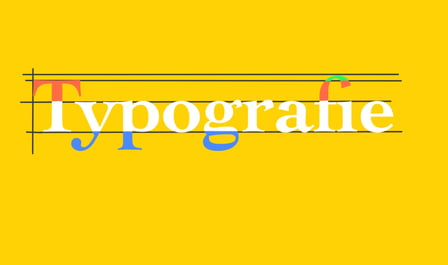
Grundlagen der Typografie | Schrift Klassifizierung | Grafikdesign
wichtige Begriffe
Anatomie der Schrift
Schriftschnitte
Schriftklassifizierungen Gruppe 1-3
Schriftklassifizierungen Gruppe 4-6
Schriftklassifizierungen Gruppe 7-9
Schriftklassifizierungen 10-11
In diesem Kurs erkläre ich euch die Grundlagen der Typografie.
zum Bespiel erkläre ich euch:
- wichtige Begriffe
- Anatomie der Schrift
- Schriftklassifizierungen